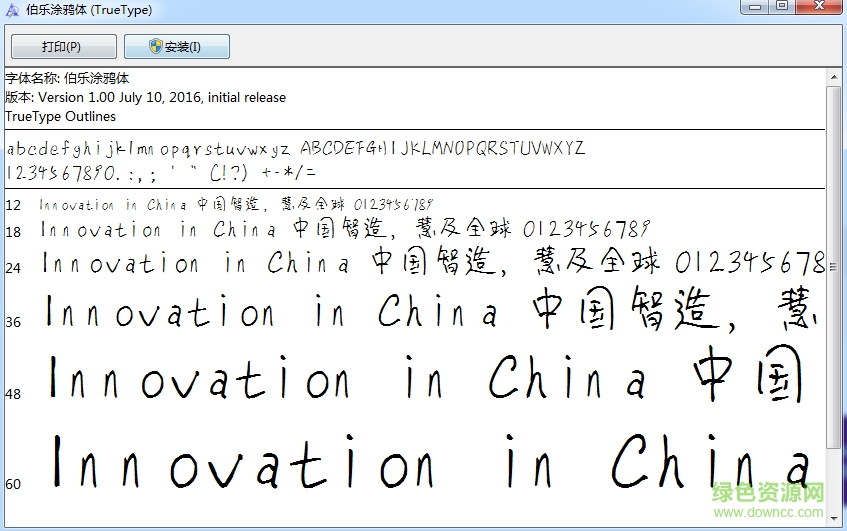
伯樂(lè)涂鴉體是一款充滿童趣的卡通手寫(xiě)體,字體線條流暢簡(jiǎn)約,如同孩子的任性涂鴉,有著稚嫩而認(rèn)真的觀賞美感,喜歡就快來(lái)綠色資源網(wǎng)下載吧!
伯樂(lè)涂鴉體是一款少兒風(fēng)卡通字體,簡(jiǎn)潔流暢的字跡讓你的打字輸入和廣告設(shè)計(jì)更有創(chuàng)意,可廣泛運(yùn)用于平面設(shè)計(jì)、海報(bào)印刷等方面。
伯樂(lè)涂鴉體 Regular Version 1.00 July 10, 2016, initial release字體(字體家族名稱:伯樂(lè)涂鴉體;字體風(fēng)格樣式名稱:Regular),共有8479個(gè)字符。